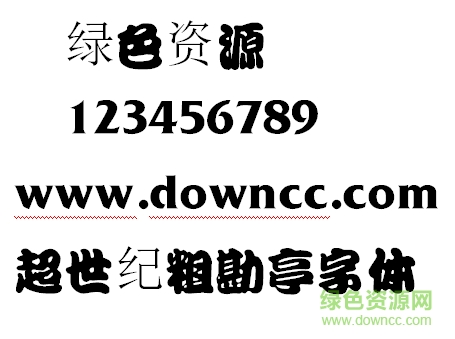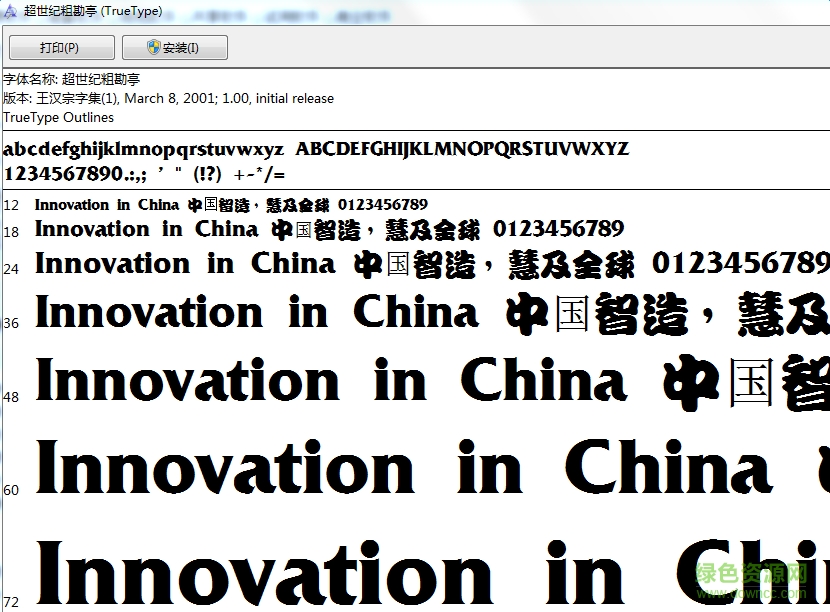
超世紀(jì)粗勘亭字體是一款為藝術(shù)美工專(zhuān)業(yè)的用戶打造的藝術(shù)字設(shè)計(jì)字體,十分好看,實(shí)用性強(qiáng),相信不多說(shuō),老司機(jī)都知道,喜歡就來(lái)下載體驗(yàn)唄!
超世紀(jì)粗勘亭是一款用于美工設(shè)計(jì)方面的字體,該字體端莊雄秀、神韻超逸、圓融蒼潤(rùn),看上去十分美觀,整體效果非常統(tǒng)一,且字庫(kù)完整,可以廣泛應(yīng)用于出版印刷、文學(xué)雜志、宣傳海報(bào)、ppt、影視制作以及內(nèi)容用字等領(lǐng)域,有需要的朋友可以免費(fèi)下載收藏。